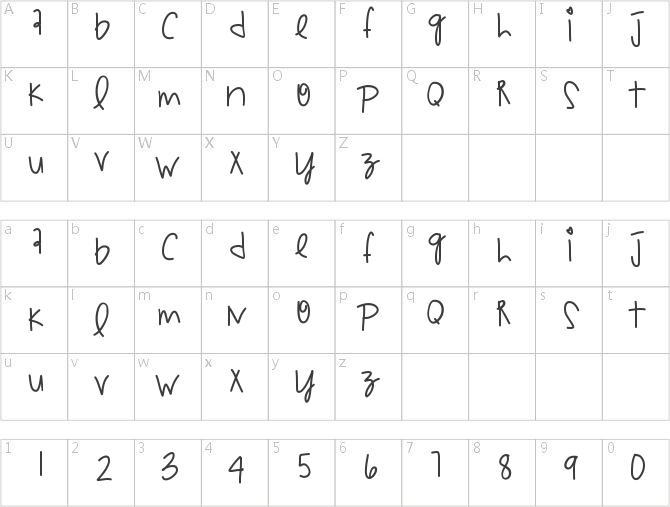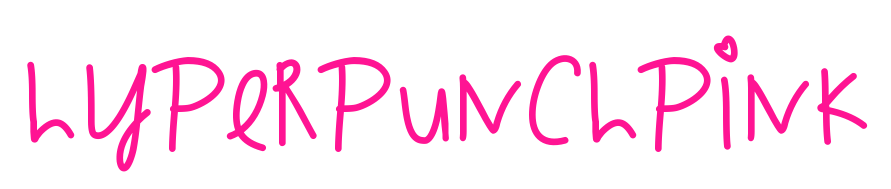
HyperPunchPink 詳情頁(yè)
HyperPunchPink字體字庫(kù)是一款讓人賞心悅目、百看不厭的英文字體,適合各類(lèi)廣告和產(chǎn)品包裝設(shè)計(jì)應(yīng)用,字體大小0.02MB,格式為ttf字體,上傳用戶(hù)是那是不變的,作者/版權(quán)方為未知